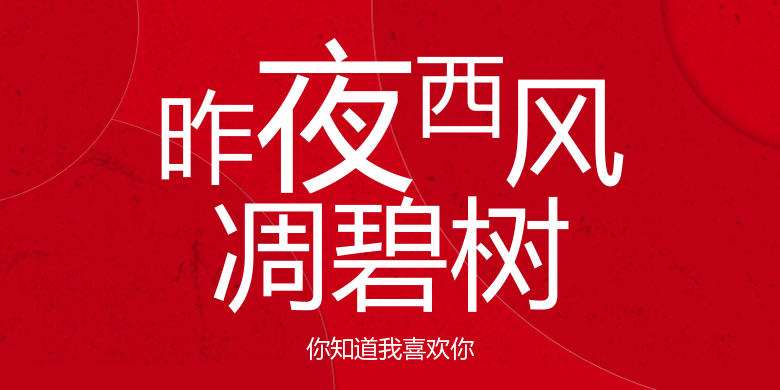
你知道我喜欢你
你知道我喜欢你,这款字体结构工整、笔画清晰,兼顾美观与易读性,适用于标题、正文、海报、包装、LOGO 等多种场景。字形优雅稳定,风格百搭耐看,适配日常排版与创意设计,让文字呈现更舒适、更具质感。你知道我喜欢你一笔一画,皆是细节,以均衡的比例、流畅的线条打造舒适视觉体验,字形端正大气,风格简约现代。无论是商业设计、品牌宣传还是日常排版,都能轻松驾驭,让文字更有格调与力量。你知道我喜欢你字体下载。